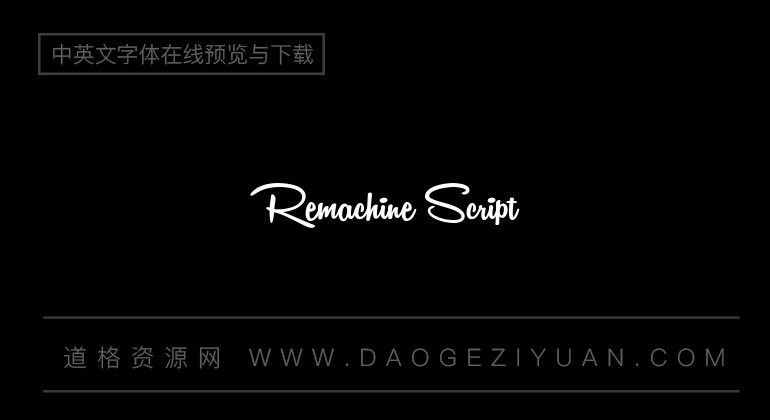
Remachine Script
Remachine Script是一种免费的手写风格字体,适用于商业和个人项目。它是由设计师Måns Grebäck创建的,该字体拥有粗大的连笔和一些波动的线条,使得它看起来非常生动和自然。Remachine Script字体的特点是它兼容多种语言,包括英语、西班牙语、葡萄牙语、德语、法语、意大利语等,这使得它在许多项目中都很受欢迎。无论是用于印刷品,还是在数字媒体上,Remachine Script都能够带来清新的个性化风格。
Remachine Script是一款非常不错的手写艺术字体,具有很好的视觉感,适合于文化类的宣传设计、商业类品牌的广告和产品包装设计以及个性化文字排版等较多场景。